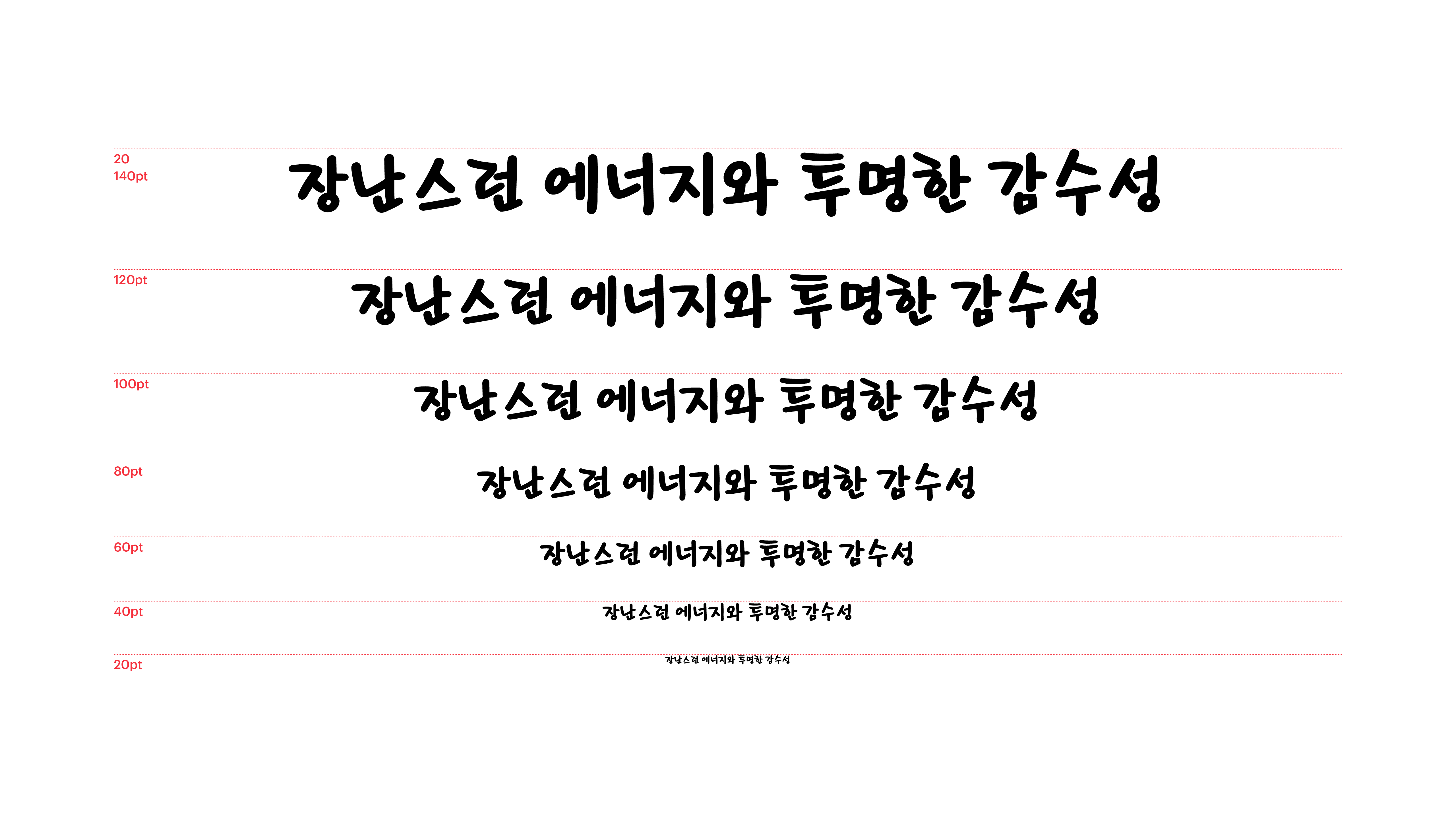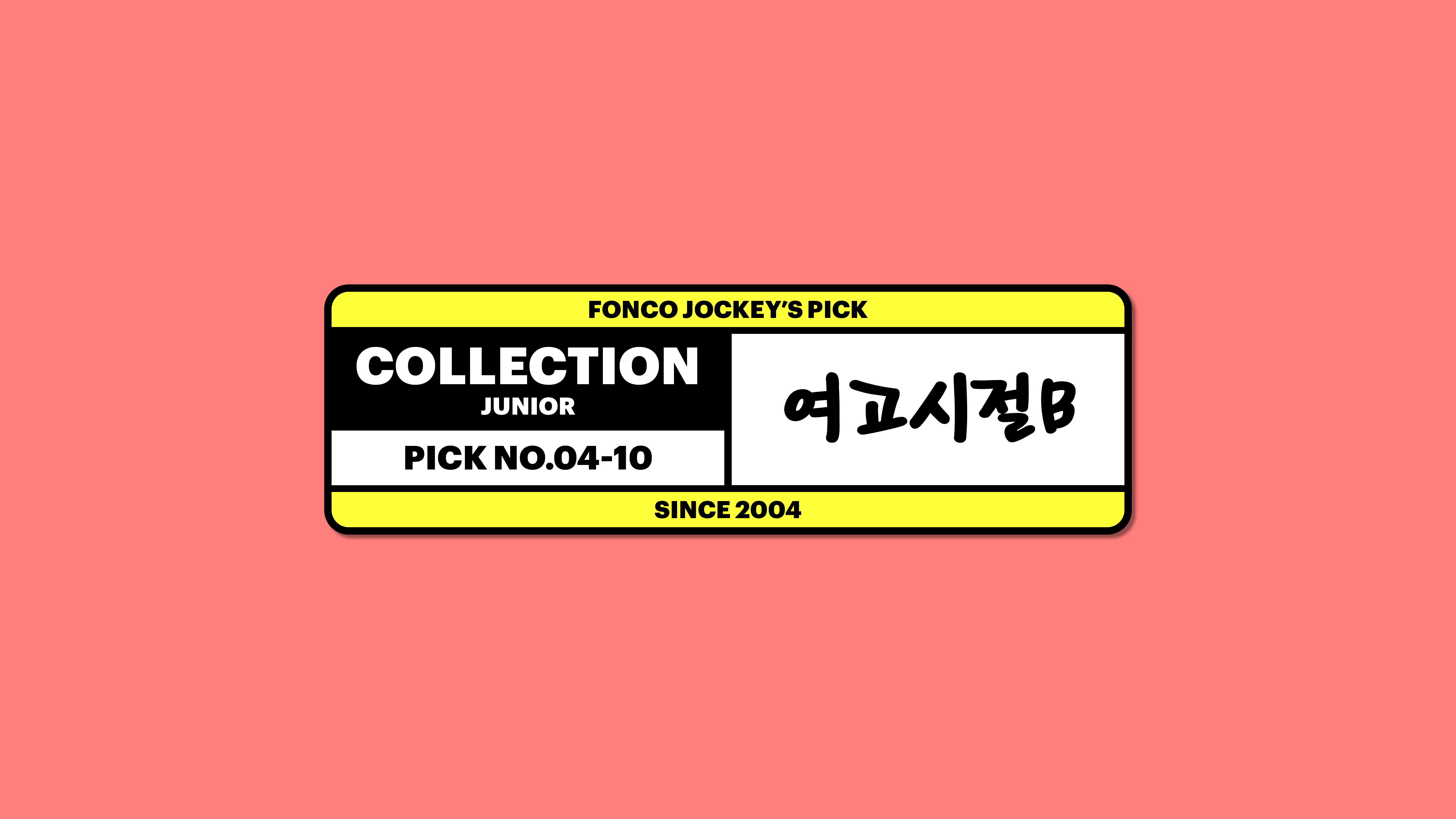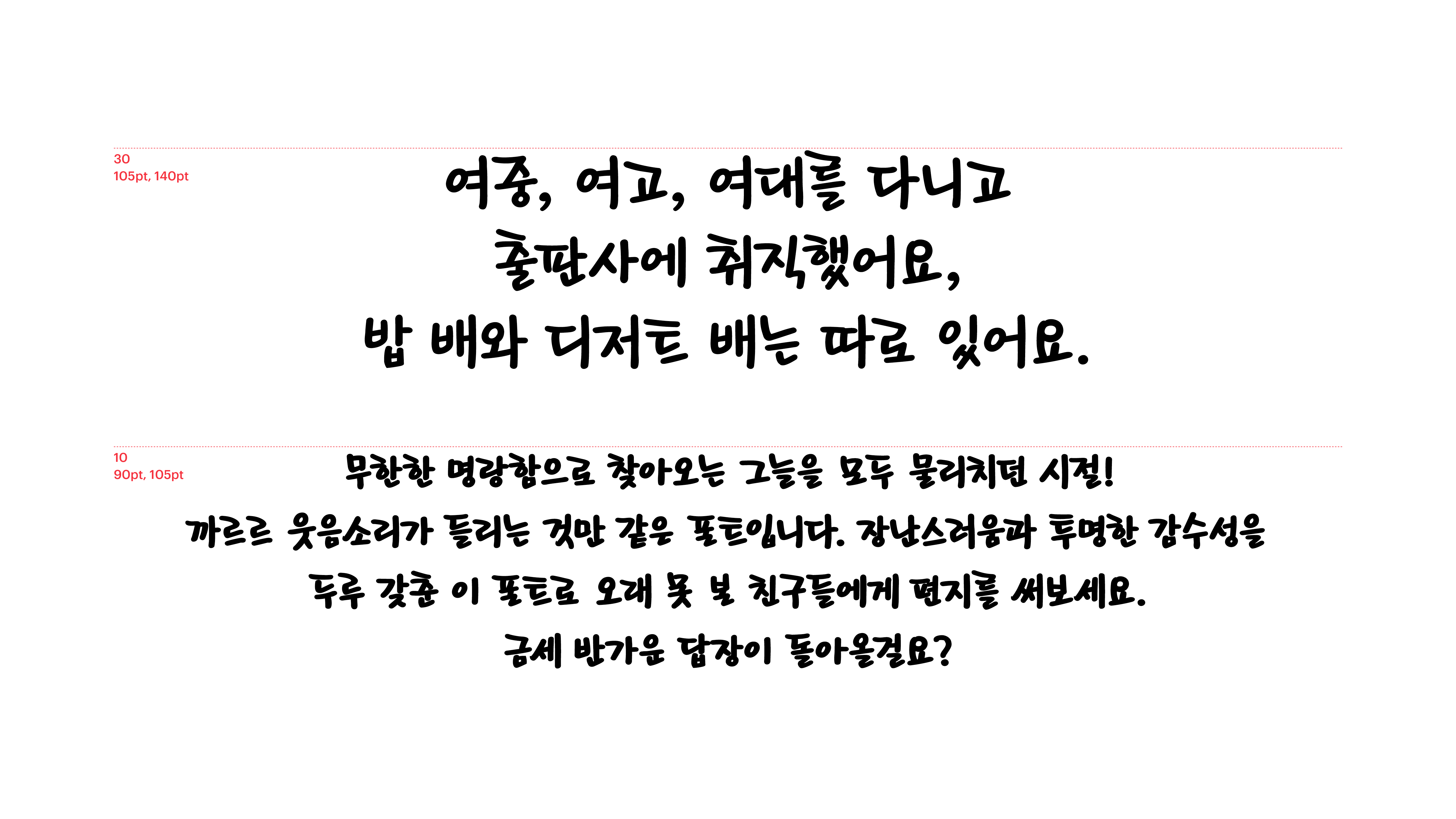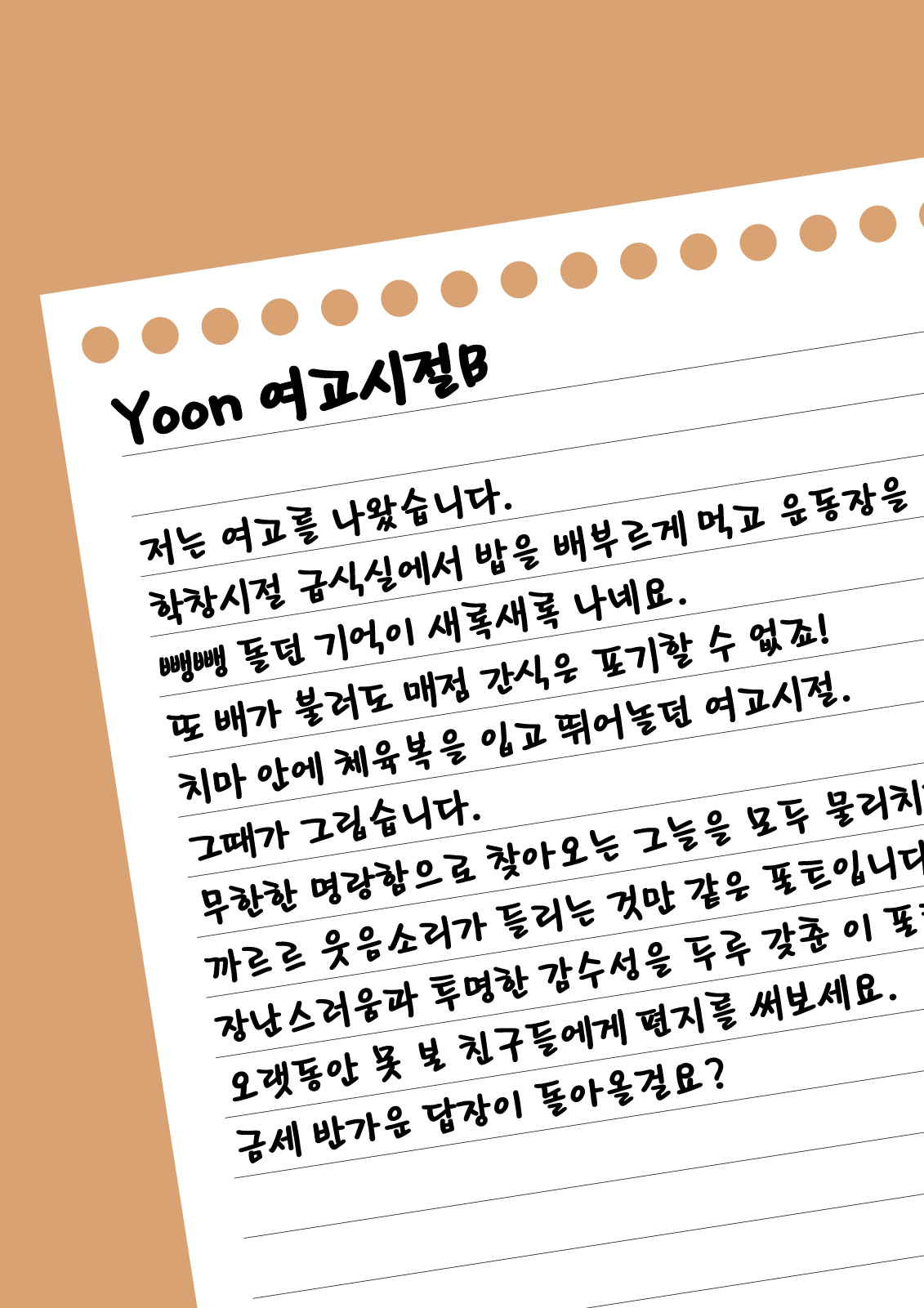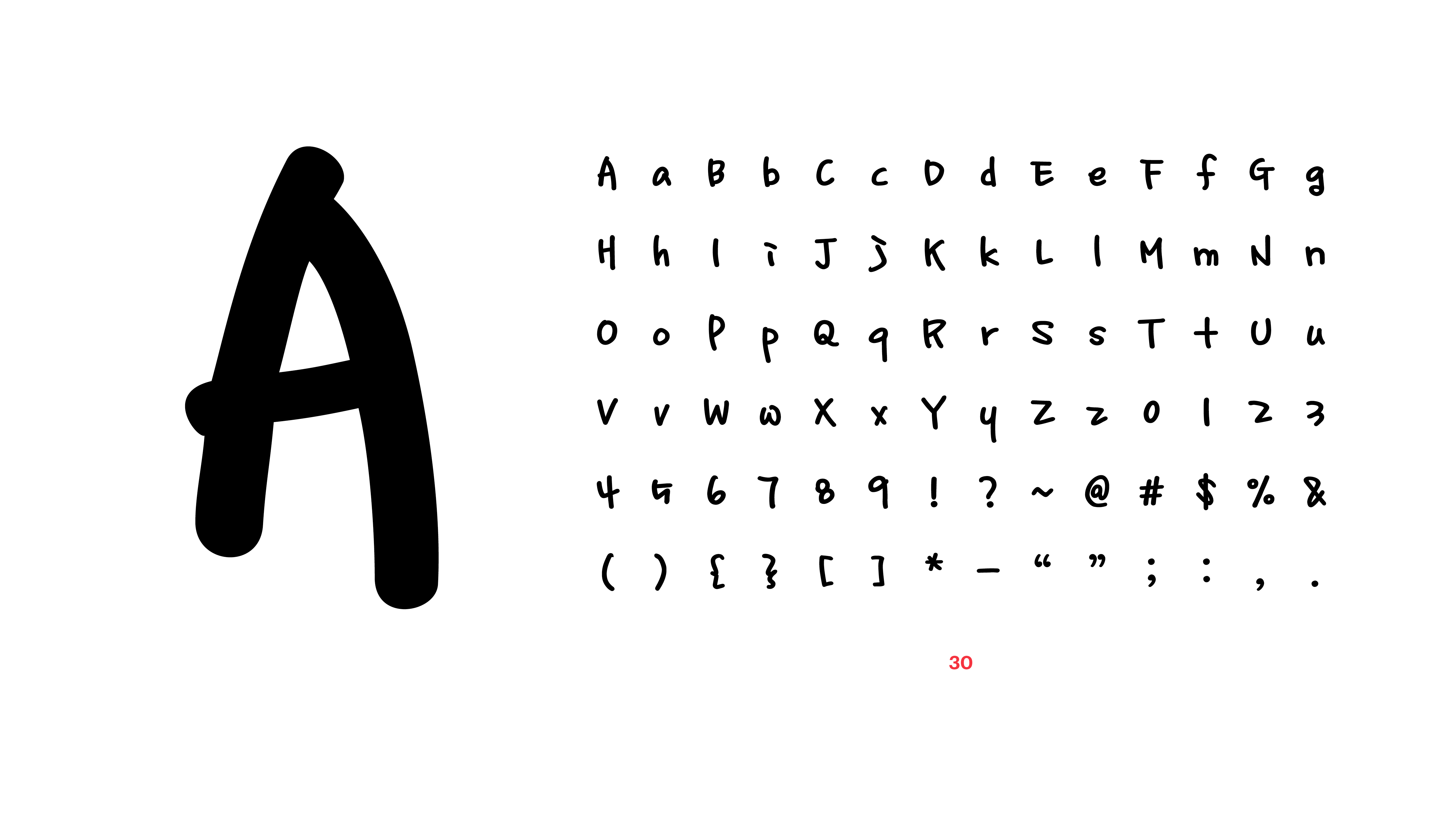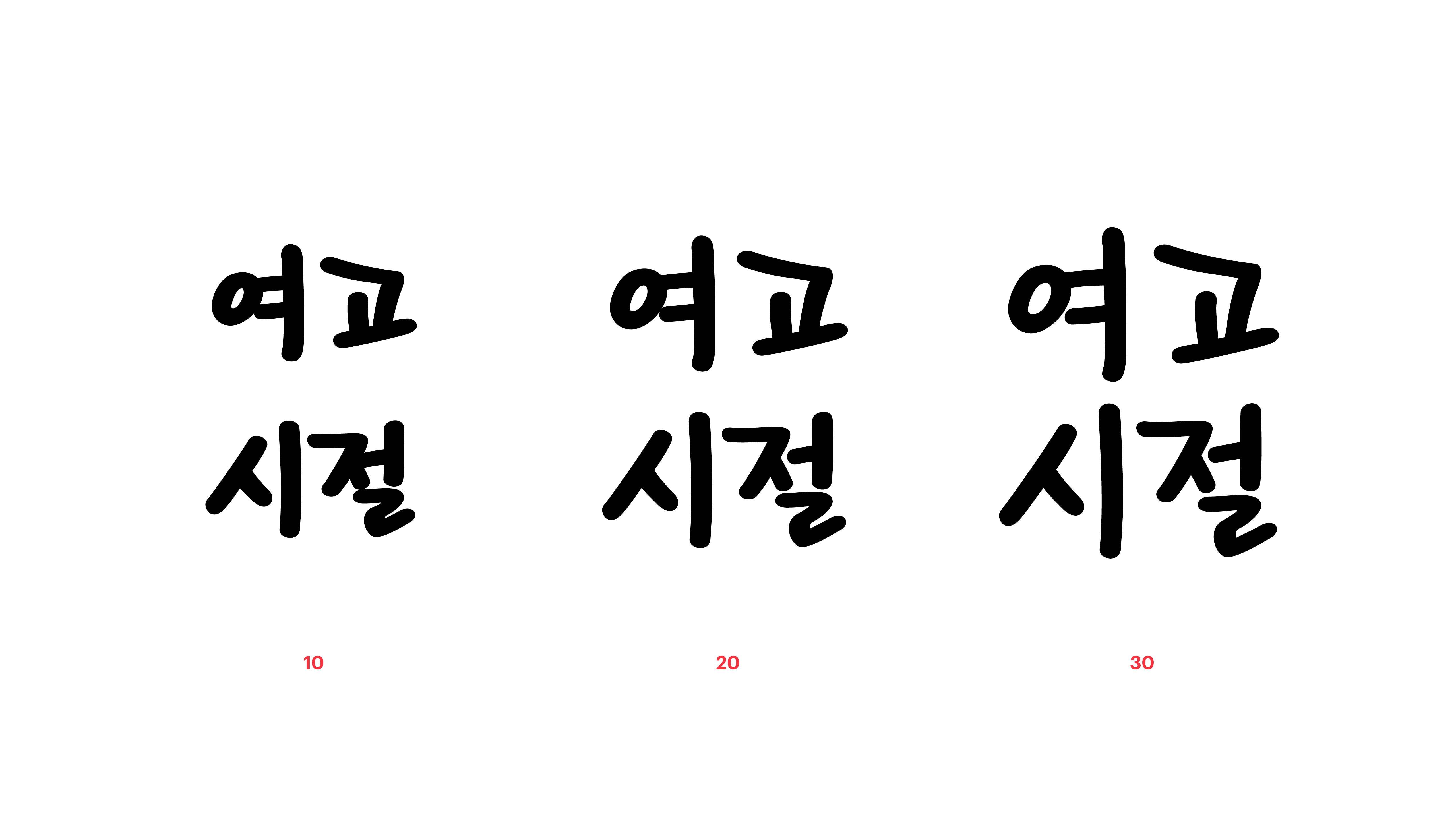
[손글씨]
여고시절B
Yoon 여고시절B
무한한 명랑함으로 찾아오는 그늘을 모두 물리치던 시절! 까르르 웃음소리가 들리는 것만 같은 폰트입니다. 장난스러움과 투명한 감수성을 두루 갖춘 이 폰트로 오래 못 본 친구들에게 편지를 써보세요. 금세 반가운 답장이 돌아올걸요?